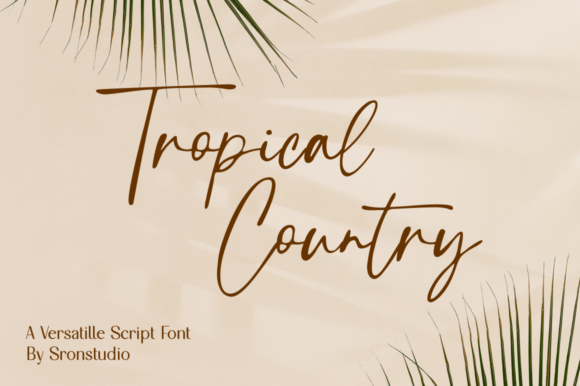
[Creativefabrica] Tropical Country Font
Tropical Country - это стильный, роскошный и легкий рукописный шрифт.
Он характеризуется плавными изгибами и идеально подходит для модного брендинга или редакционного дизайна.